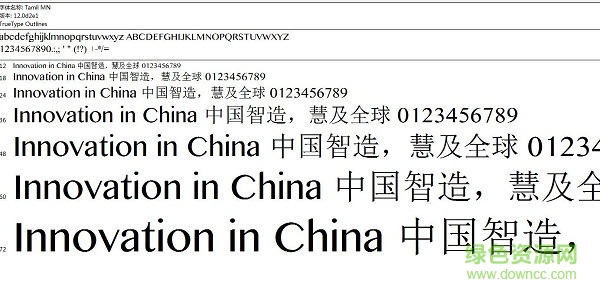
tamilmn字體包括regular和bold兩種字型,該字體是一款印度泰米爾語(yǔ)字體,由馬來(lái)西亞字體公司Murasu推出,整體設(shè)計(jì)水平還行,需要的朋友歡迎在本站免費(fèi)下載!
泰米爾語(yǔ),是一種有超過(guò)二千年歷史的語(yǔ)言,屬于達(dá)羅毗荼語(yǔ)系,通行于印度南部、斯里蘭卡東北部。它是泰米爾納德邦的通用語(yǔ),斯里蘭卡的一種官方語(yǔ)言。根據(jù)統(tǒng)計(jì),在1996年,泰米爾語(yǔ)在全球的語(yǔ)言人口中排第18位,有語(yǔ)言人口7,400萬(wàn)人。
分布于泰米爾納德邦,使用人口約3500萬(wàn)。此外,也使用于斯里蘭卡部分地區(qū)(約250萬(wàn)人),在東南亞、東非、南非、印度洋和南太平洋中的島嶼,也有少數(shù)人使用。